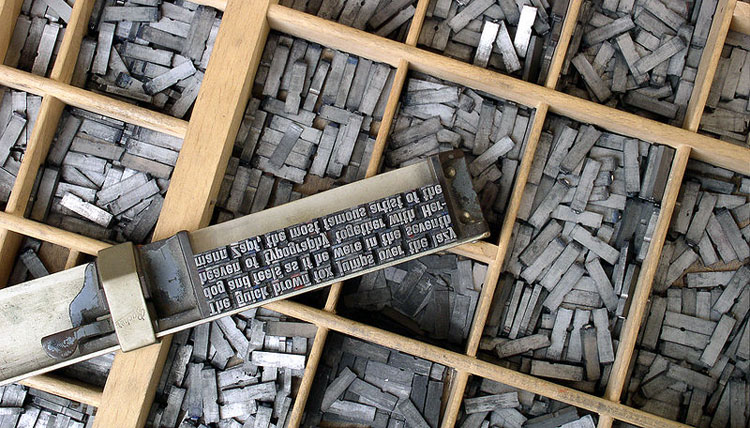
La tipografía
La tipografía (del griego τύπος typos, golpe o huella, y γράφω graphο, escribir)
es el arte y técnica del manejo y selección de tipos, originalmente de plomo, para crear trabajos de impresión.
El tipógrafo Stanley Morison la definió como:
«Arte de disponer correctamente el material de imprimir, de acuerdo con un propósito específico: el de colocar las letras, repartir el espacio y organizar los tipos con vistas a prestar al lector la máxima ayuda para la comprensión del texto.»
Stanley Morison, Principios fundamentales de la tipografía (1929)
Hay que entender por tipografía, en sentido estricto, el diseño con tipos de letra disponibles; no comprende, por tanto, ni la caligrafía, ni el diseño de alfabetos tipográficos, ni el «letering»(Dibujo de letras).
Macrotipografía y microtipografía
Macrotipografía:
La concepción, el proyecto,la idea, el diseño en general. Aquí se incluye la elección del formato, del tipo de letra, de los colores, del papel; luego la composición de las páginas y, en trabajos que abarcan varías páginas la compaginación.
Microtipografía:
Comprende todo lo relacionado con el espacio entre los caracteres, las palabras y la líneas. Es decir los detalles de la composición tipográfica.
(del libro Primeros auxilios en tipografía de Hans Peter Willberg y Friedrich Forssman)
Tipografía de Edición vs Tipografía Creativa
Tipografía de edición
Reúne las cuestiones tipográficas relacionadas con las familias, el tamaño de las letras, los espacios entre las letras y las palabras; interletrado e interlínea y la medida de línea y columna o caja, es decir aquellas unidades que conceden un carácter normativo. (Manual de tipografía, del plomo a la era digital).
Tipografía creativa
Esta contempla la comunicación de otro modo, como si se tratara de una metáfora visual, donde el texto no sólo tiene una funcionalidad lingüística, y donde a veces, se representa de forma gráfica, como si se tratara de una imagen. (Manual de tipografía, del plomo a la era digital). (Ver más)
Familia, fuente, tipo,…